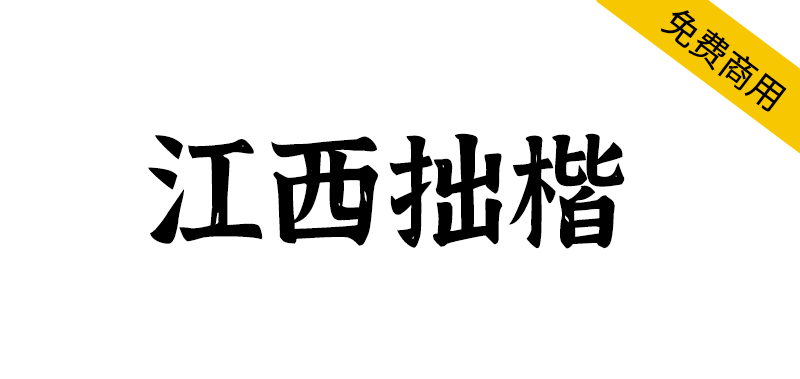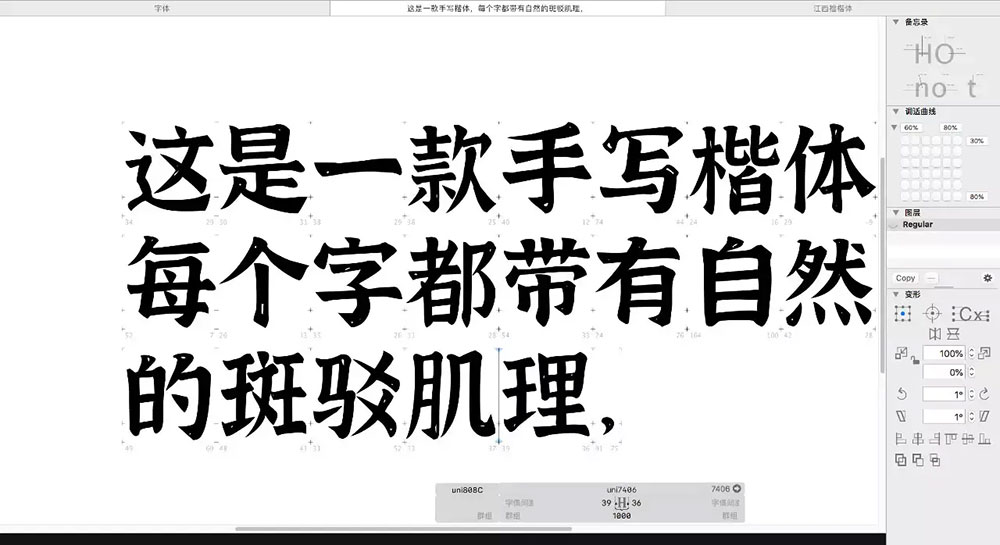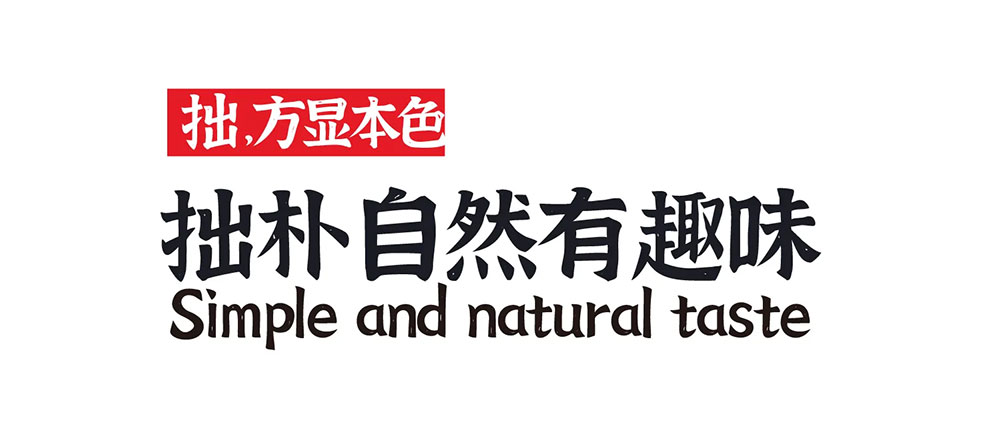
大家好,我是黄煜臣,我个人第一套字体,今天正式跟大家见面了。第一套字体的发布我很重视,自己花了那么大精力去做这件事,今天终于有了一个阶段性成果,此时内心既有点小激动还有些忐忑,我不知道发布后会有什么效果,大家是喜欢还是无感?会不会带着期待而来,又失望而去?不过俗话说的好,丑媳妇终得见公婆,藏着掖着不敢露脸肯定是不行的,敢于直面不同眼光的评判才是勇敢者的做法,说不准会有人喜欢这个丑媳妇。
这是一套手写楷体,相比电脑中标准化制作的楷体,这套字体的笔画会带有一些书写的痕迹,每个字的笔画是没有统一标准的,所以看上去显得不够规范,但是会有一种手写的自然之感。这套字体从写手稿开始到今天的最终成品,前前后后花了近半年时间,仅仅是调节点,就花了20多天,其中的滋味做过才知道。
这套字体从手稿到成品,中间经过了无数次的修改调整,与最初字形相差挺大。对于这款字体的发布,我不希望仅仅就是一款字体的展示,我希望它能发挥更大的作用,带来一些其他的价值,为了达到这个目的我想了很久——最终决定用这款字体为我们大江西做宣传。江西在各省市一直是一种低调的存在,不管是经济发展还是对外传播都是比较滞后的,我作为江西人,现在还没有能力用真金白银去为家乡做贡献,但是我可以用我的一点专业技能来为江西打打广告,做做宣传,希望让更多人认识他,喜欢他。
你可以试试用这个字体来做印章,会有意想不到的效果,跟印章的斑驳肌理很契合。也可以试试用在文创产品上, 比如帆布袋,手机壳。这款字的性格和江西很像, 低调内敛,朴实无华毫不张扬!就命名为江西拙楷,希望通过这套字体让江西增加点曝光度,让更多人了解江西。